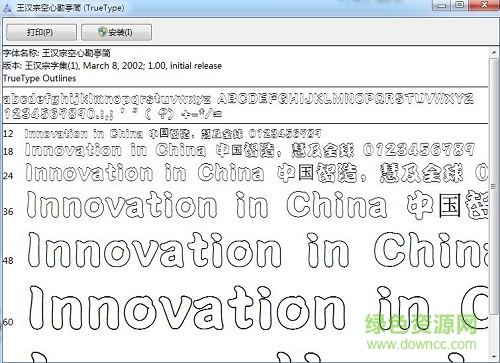
王漢宗空心勘亭簡是一款王漢宗根據(jù)勘亭流體打造的藝術字體,該字體不僅延續(xù)了勘亭流體的所有特色,還采用空心的方式,讓字體更加充滿藝術性,有需要的朋友歡迎下載!
王漢宗空心勘亭簡是一款空心的勘亭流體字體,字體筆畫中極少出現(xiàn)直線與折角,幾乎全由曲線和彎角構(gòu)成,形成了其特有的藝術效果,被廣泛應用于表現(xiàn)日式風格的招牌、標題、包裝等上面,倍受廣大平面設計者的青睞。